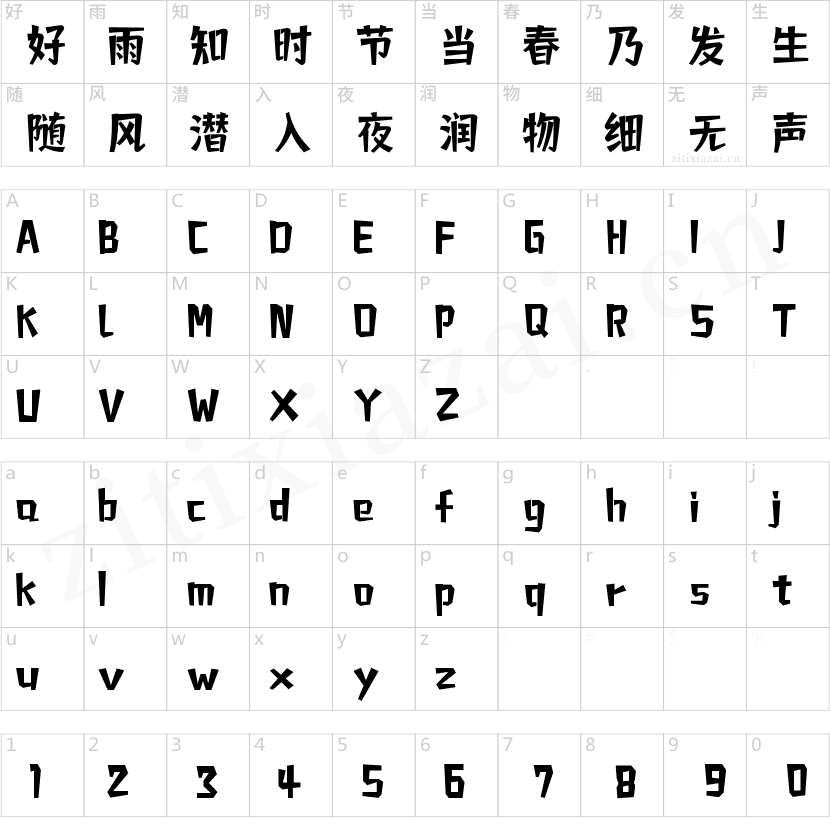
字魂时光机
字魂时光机,这款字体结构工整、笔画清晰,兼顾美观与易读性,适用于标题、正文、海报、包装、LOGO 等多种场景。字形优雅稳定,风格百搭耐看,适配日常排版与创意设计,让文字呈现更舒适、更具质感。字魂时光机一笔一画,皆是细节,以均衡的比例、流畅的线条打造舒适视觉体验,字形端正大气,风格简约现代。无论是商业设计、品牌宣传还是日常排版,都能轻松驾驭,让文字更有格调与力量。字魂时光机字体下载。
字魂字体字魂时光机字体是由字魂创意字库设计并生产的一款可商用的字体,被收录于字魂先锋系列。该字体支持GB-2312标准,包含6765个中文、字母、符号和数字,字体类型偏向卡通可爱,具有活泼、动漫、可爱的风格,在市面上广泛用于媒体&H5、游戏、社交等场景。